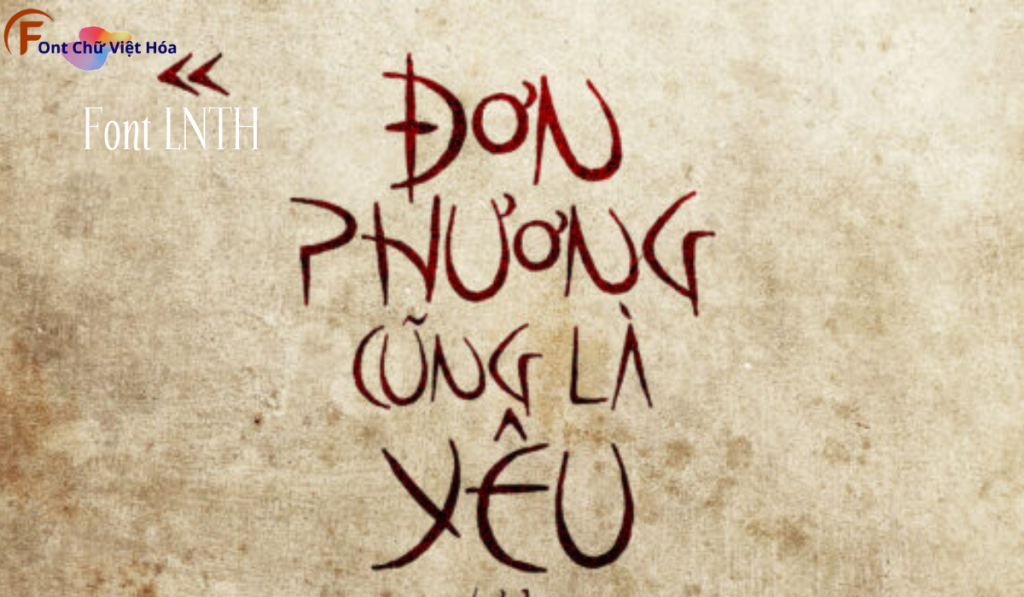
Font LNTH Poseidon AOE Việt Hóa
Tác giả: LNTH
Bộ Font: LNTH
Phân loại: Cá tính, Độc đáo
Font LNTH Poseidon AOE Việt Hóa là một font chữ mạnh mẽ, thuộc bộ LNTH, với thiết kế đậm chất thể thao và hiện đại. Phong cách của font này phù hợp với các dự án cần sự mạnh mẽ và năng động, như logo, tiêu đề, hoặc bảng hiệu. Font LNTH Poseidon AOE Việt Hóa mang đến sự mạnh mẽ và dễ nhận diện, ứng dụng trong các lĩnh vực sáng tạo. Đặc điểm hình dạng của font bao gồm các đường nét dày và sắc sảo, giúp tăng tính thẩm mỹ và sự chú ý. Việc Việt hóa font giúp người dùng dễ dàng sử dụng trong các thiết kế tiếng Việt, mang lại sự tiện lợi và linh hoạt.